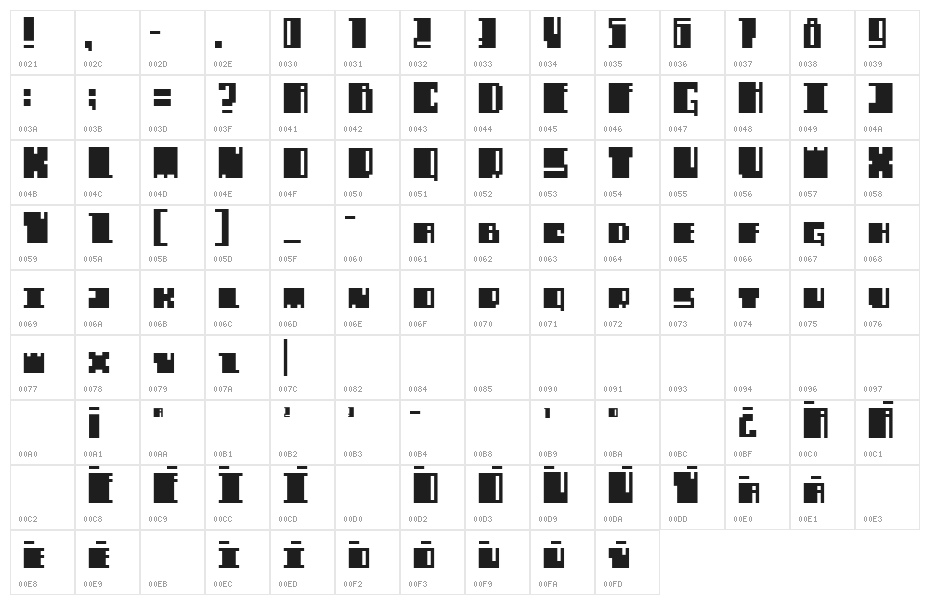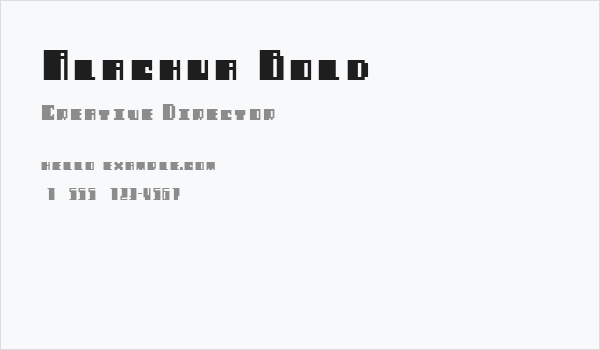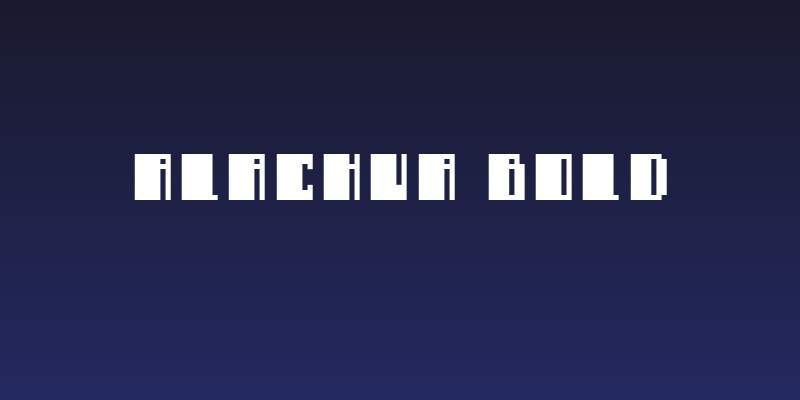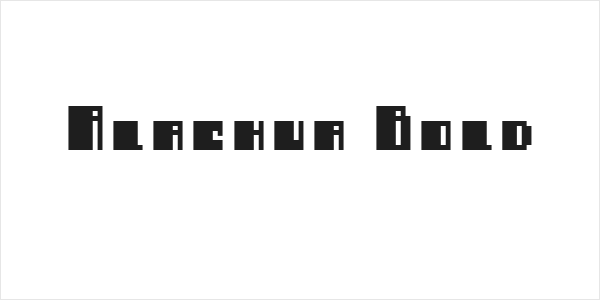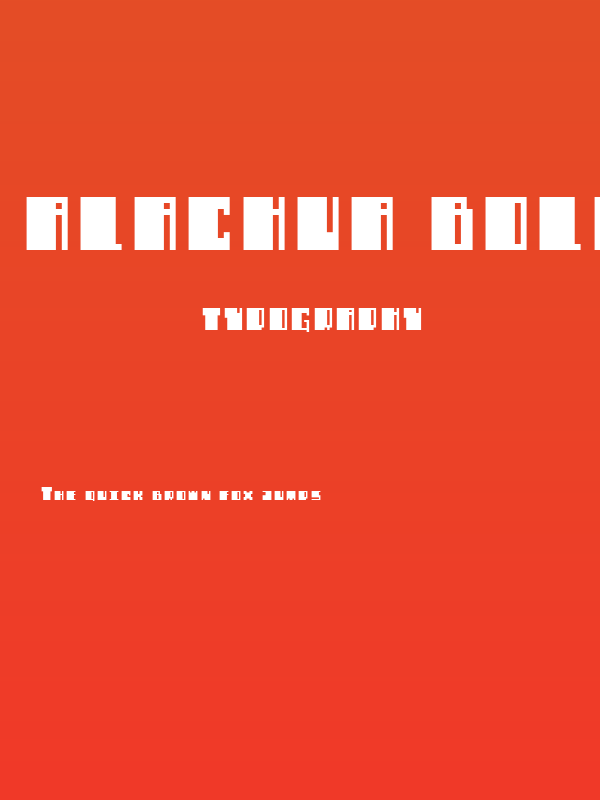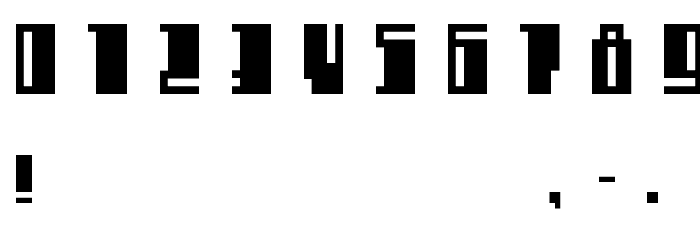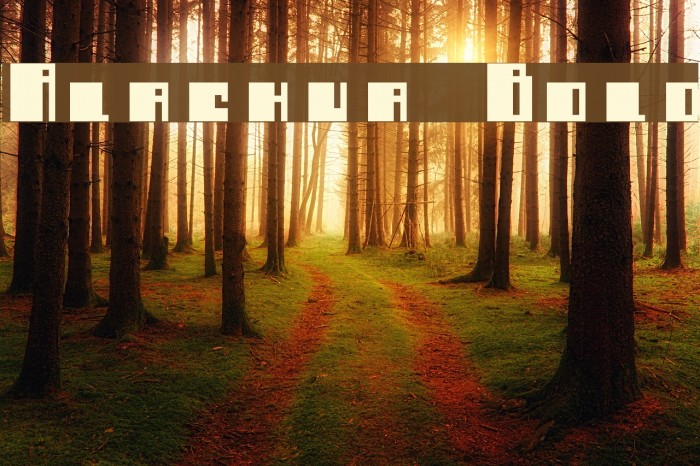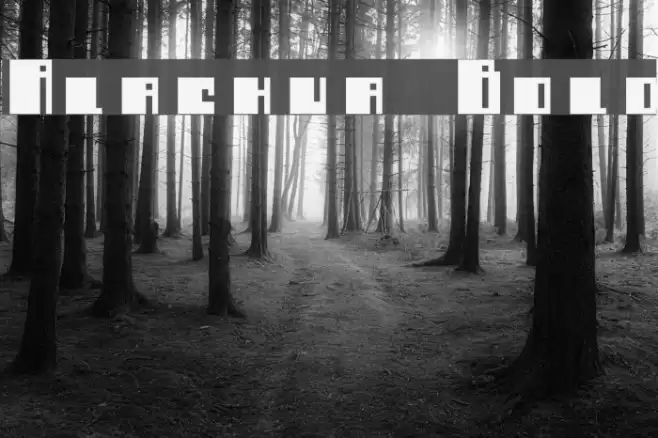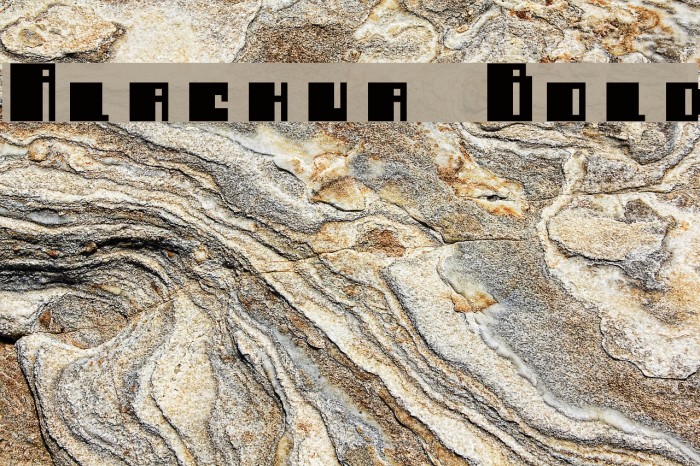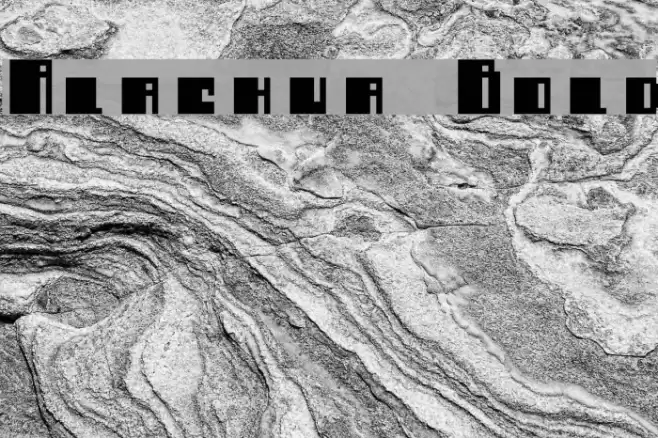
Alachua Bold Font
| Stil general | Retro, Digital |
| Proiecte propuse | Ideal for video game designs, retro-themed posters, digital art projects, and any creative work that seeks a nostalgic or tech-inspired look. |